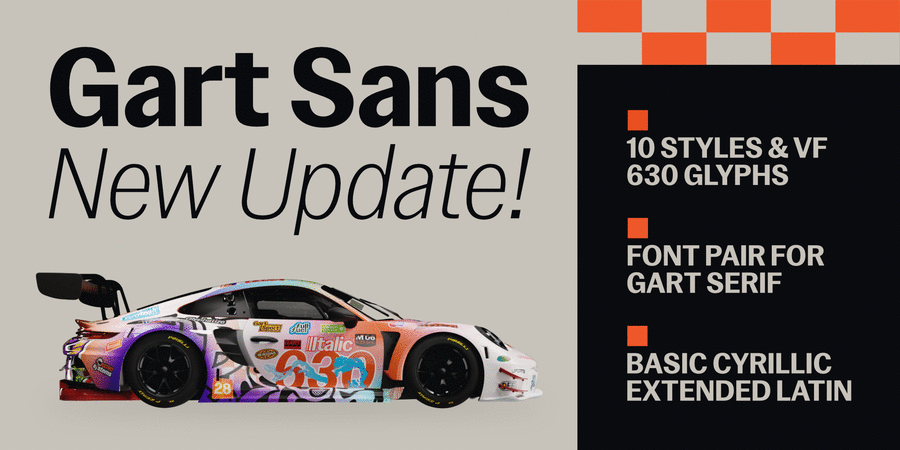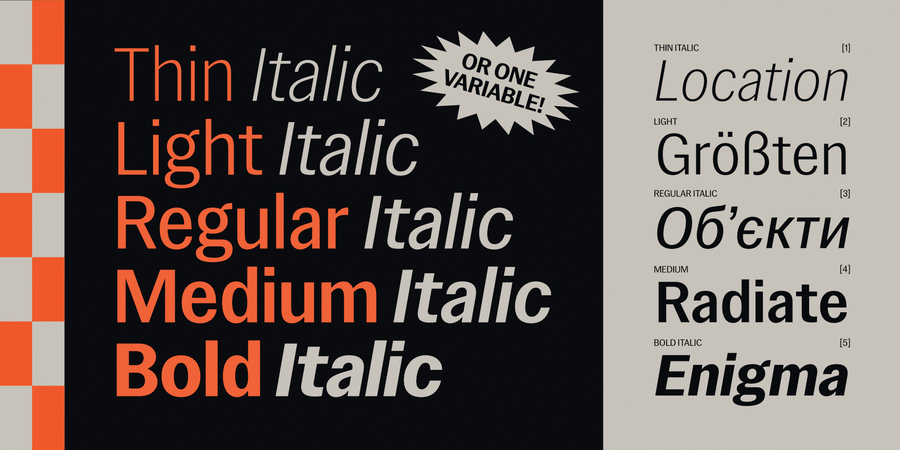
Gart Sans — це гарнітура, яка зберігає риси ранніх гротесків 20-го століття, які в основному використовувалися в рекламі. Головними особливостями цього шрифту є виразний контраст, вузькі пропорції і легкі плавні форми в поєднанні з сучасними рішеннями. Gart Sans — це ідеальна шрифтова пара для Gart Serif.
Порівняно з геометричними гротесками чи неогротесками, Gart Sans вирізняється характерними деталями. Вузькі пропорції дозволяють гнучкіше працювати в різному середовищі, легкий контраст додає виразності набраному тексту, що добре простежується зі збільшенням ваги. Шрифт чудово підходить для заголовків і набору великого обсягу тексту. Oкрім статичних накреслень, Gart Sans має також варіативний шрифт, що розширює його можливості використання. Gart Sans складається з 10 накреслень, 630 гліфів, курсиву з кутом нахилу в 10°, включає розширений набір латиниці, базову кирилицю, лігатури, набори цифр і багато іншого. В оновленні додано курсив з кутом нахилу 10° до кожного накреслення, що робить гарнітуру ще динамічнішою; також покращено загальний контур та кернінг. Гарнітуру Gart Sans розробив Віталій Гоцанюк у 2023 році, та оновив у 2024. Світ ловив мене, та не спіймав!
11 накреслень
Особливості сімейства шрифтів Gart SansХіт десятиліття:
Хіт 1950-х Хіт 1960-х Gart Sans підтримує 83 мовиУкраїнська, Англійська, Німецька, Польська, Португальська, Іспанська, Французька, Російська, Чеська, Голландська, Італійська, Шведська, Турецька, Фінська, Білоруська, Сербська, Болгарська, Естонська, Литовська, Албанська, Африкаанс, Баскська, Бретонська, Валенсаска, Galician, Гельська (Шотландська), Данська, Індонезійська, Ірландська, Ісландська (Win), Каракалпацька, Каталонська, Норвезька, Окситанська, Ретороманська, Самі Лулі, Тсванська, Узбецька (Лат.), Фарерська, фризька, Чаморро, Естонська (Win), Південносаамська, Албанська (Win), Угорська, Верхньолужицька, Карельська, Латвійська (Mac), Литовська (Mac), Маорійські (Mac), Молдавська (Лат.), Нижньолужицька, Румунська (Win), Словацька, Словенська, Туркменська (Лат.), Хорватська (Win), Естонська (Mac), Курдська, Латишська, Маорійські, Руминська, Абазинська, Аварська, Агульська, Адигейська, Даргинську, Інгуську, Кабардино-Черкеська, Кабардинська, Карачаєво-Балкарська, Кумицька, Лакська, Лезгинська, Македонську, Мордовсько-Мокшанська, Мордовсько-Ерзянська, Ногайська, Рутульська, Табасаранська, Татська, Цахурська, Чеченська Функції сімейства шрифтів Gart SansЗастосування гарнітури у верстці: